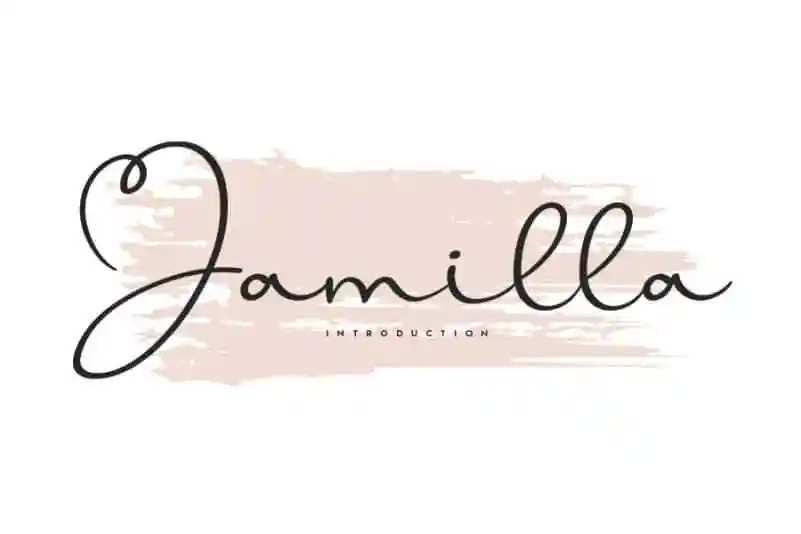
Jamilla Handwritten Font – Download Grátis
A Jamilla Handwritten Font é uma deliciosa mistura de letras cursivas redondas e suaves. Seu estilo distintivo e suave transmite beleza natural, adequado para um vasto número de projetos. Esta fonte não apenas combina perfeitamente com estilos decorativos e artísticos, mas também se destaca em design simples e minimalista. Agradável aos olhos, a Jamilla Handwritten Font é perfeita para criar mensagens pessoais, cartões de aniversário personalizados, recados criativos ou qualquer outro projeto que você possa imaginar. Seja para uma campanha publicitária sofisticada ou um design de site minimalista, a fonte se destacará por sua suavidade e elegância inconfundível.